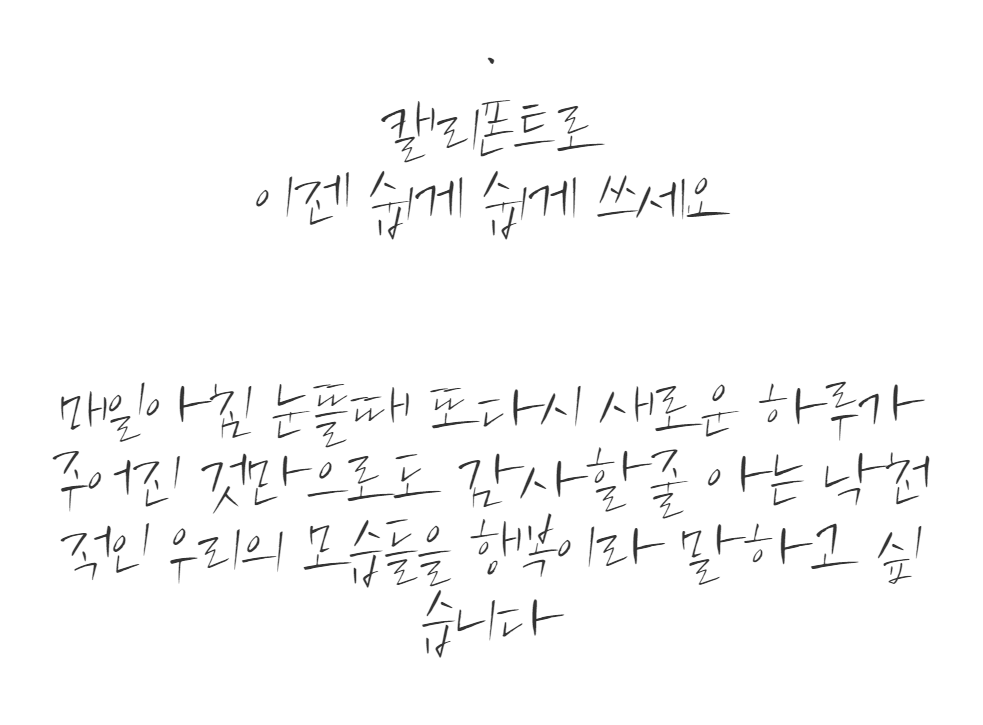
무료폰트(손글씨) : 쿨가이폰트, 쿨가이체
시원한 느낌을 주며 획이 살아있는 느낌의 쿨가이체는 깔끔한 테두리라인의 디자인작업물에 최적화된 폰트로 자유로운 개성이 살아있는 손글씨 폰트입니다. 다운로드방식을 지원하기 때문에 링크를 기록해 두었습니다. 자유롭게 다운받아 사용해 보세요